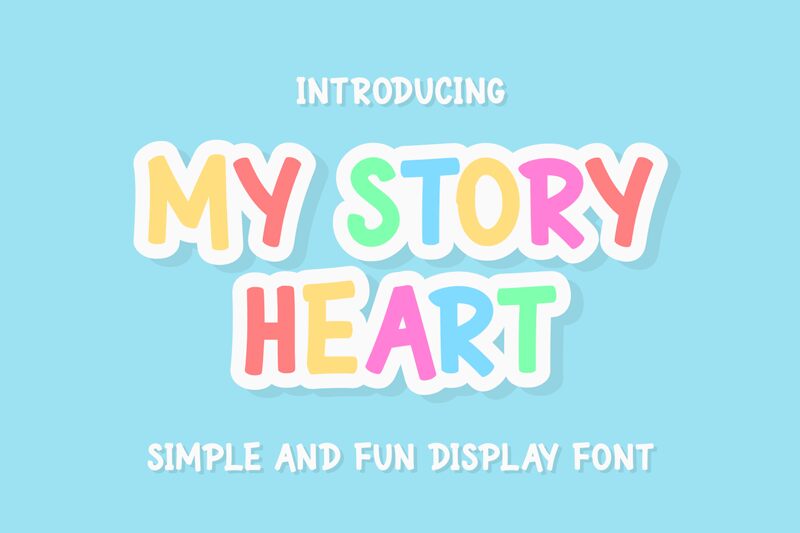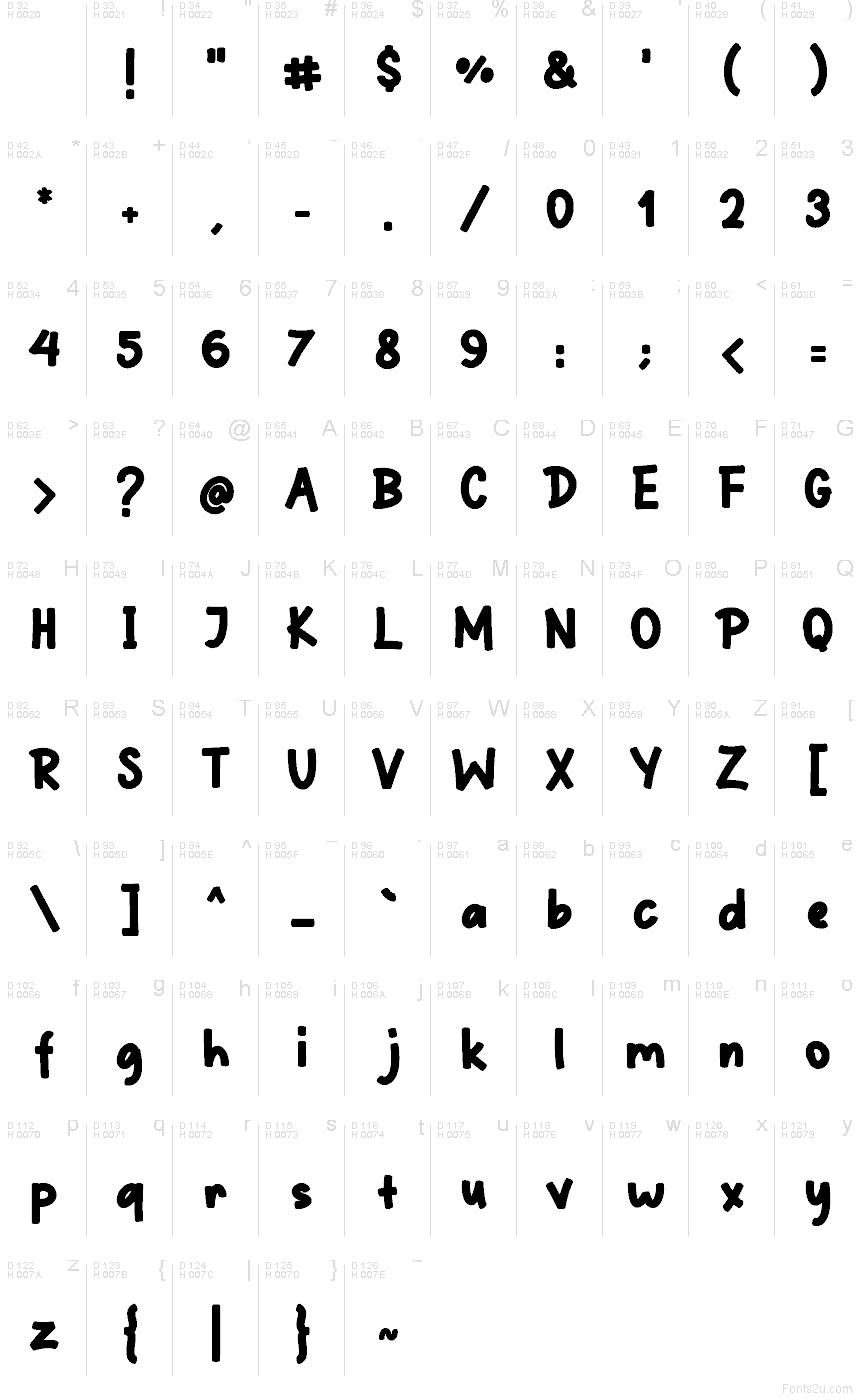
Písmo My Story Heart od MaqsumKS je bezplatný komiksový font so zaoblenými, ručne kreslenými písmenami a mäkkými, nepravidelnými okrajmi. Jeho tvary pôsobia uvoľnene a živé, s otvorenými krivkami a rytmom skicára, vďaka čomu texty nepôsobia príliš upäto.
Tento bezplatný font skvele funguje v detských knihách, na pohľadniciach, plagátoch, kreatívnych štítkoch či v príspevkoch na sociálne siete, pretože jeho neformálny charakter dodáva krátkym textom ručne písaný dojem. My Story Heart sa hodí aj na detaily v logách, nadpisy pozvánok alebo hravé balenia, keď hľadáte písmo, ktoré pôsobí osobne a nie formálne.